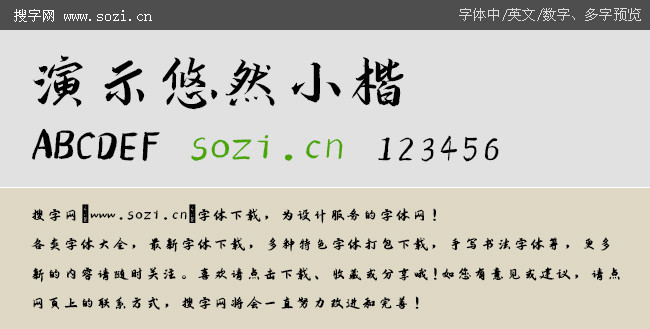
演示悠然小楷
搜字網(wǎng)給大家提供一款演示悠然小楷中文字體下載,本字體作者為孟祥媛,生于 1999 年的孟祥媛,是一位目前還在大學就讀的書法專業(yè)的學子。悠然小楷筆畫分明,結(jié)構(gòu)清晰,沒有過度的連筆和飛白,對閱讀識別更為友好;在小楷的基礎(chǔ)上有些行楷的影子,為字體增添了靈動,但又有克制,形成停而不斷、筆斷意連之態(tài);且面向全社會發(fā)布,全渠道免費商用!